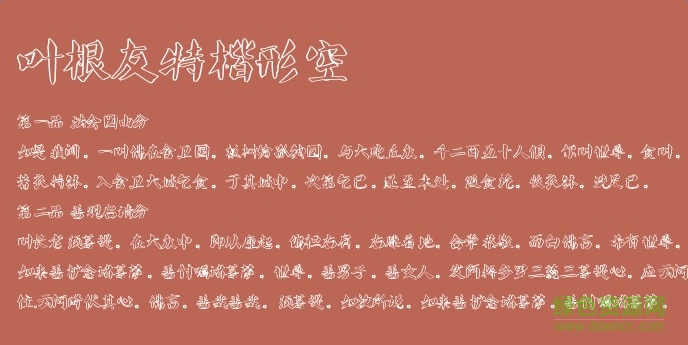
葉根友特楷形空字體是一款古典立體風(fēng)格字體軟件,特楷形空體工整粗大配上空心的筆畫,創(chuàng)意十足,十分俏皮,非常受年輕人的熱愛與追捧,還有更多好看字體歡迎來綠色資源網(wǎng)下載體驗!
葉根友特楷形空字體用于形空設(shè)計方面的字體,這款字體是以行楷字體為原形,字體以獨特的邊框設(shè)計樣式,展現(xiàn)了立體感,獨特的手寫風(fēng)格和俏皮的樣式,使字體看起來個性時尚。字體適用于廣告設(shè)計、創(chuàng)意設(shè)計、藝術(shù)設(shè)計等方面。
該字體筆畫空心,非常有立體感,在黑板報方面有著不錯的應(yīng)用,創(chuàng)意十足!